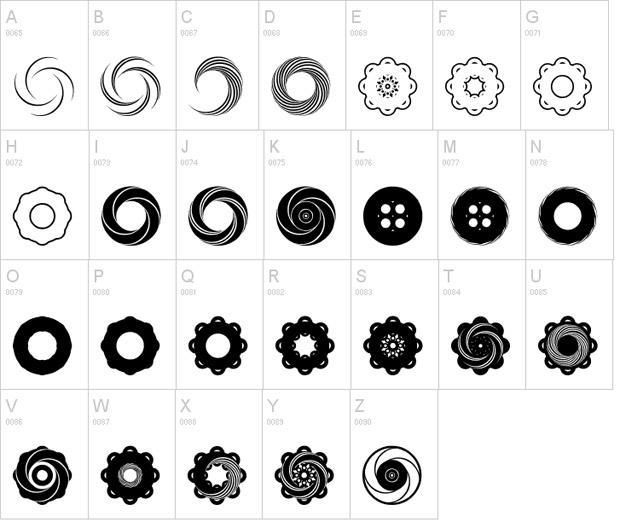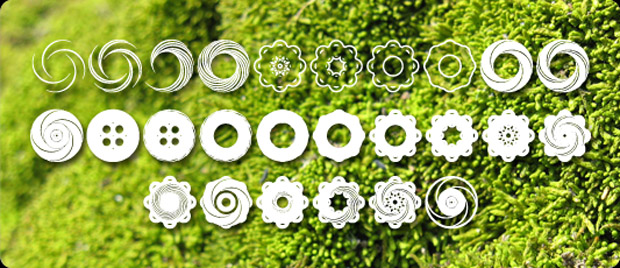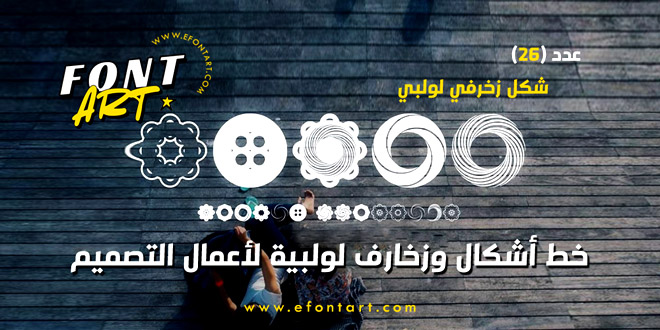
خط أشكال وزخارف لولبية لأعمال التصميم .. عبارة عن أشكال زخرفية دائرية لولبية تستخدم في كافة أعمال التصميم، وتعمل بالحروف الإنجليزي الكبيرةة والصغيرة مثل ما هو موضح في الصورة.